Combinación Efectiva de Tipografías en Carteles
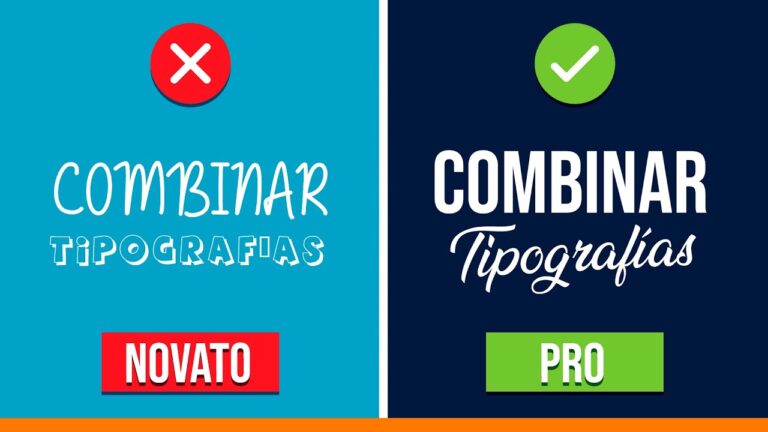
La combinación de tipografías en carteles es un arte que puede transformar un mensaje ordinario en una obra visual impactante. Al seleccionar cuidadosamente diferentes tipos de letras, los diseñadores pueden crear contrastes y armonías que capturan la atención del público y comunican emociones de manera competente. En un mundo donde la información abunda, dominar esta técnica se vuelve esencial para destacar y transmitir ideas con claridad y creatividad. En este artículo, recorreremos los principios fundamentales y las mejores prácticas para lograr combinaciones tipográficas que no solo informen, sino que también inspiren.
¿Qué tipo de letra se utiliza para carteles?
La tipografía Helvética se ha consolidado como una de las opciones más populares para la creación de carteles publicitarios. Su diseño limpio y moderno la hace destacar, autorizando que el mensaje se comunique de manera competente y rápida. Con una amplia variedad de variantes, esta tipografía se adapta a diferentes estilos y temáticas, ofreciendo flexibilidad a los diseñadores.
Además de su versatilidad, la Helvética se caracteriza por su excelente legibilidad, un aspecto decisivo para captar la atención del público. En el mundo de la publicidad, donde cada segundo cuenta, la facilidad con la que se puede leer un cartel puede marcar la diferencia entre atraer a un cliente o pasar desapercibido. Por estas razones, Helvética sigue siendo la elección preferida para muchos profesionales del diseño gráfico.
¿Qué tipografía se puede combinar con Bodoni?
Bodoni es una tipografía clásica y elegante, ideal para títulos que buscan destacar. En contraste, Montserrat aporta un toque moderno y fresco, convirtiéndose en una opción popular en el diseño contemporáneo. Juntas, estas tipografías crean una combinación sofisticada y armoniosa, donde la elegancia de Bodoni se complementa perfectamente con la ligereza y legibilidad de Montserrat, logrando un equilibrio visual atractivo y efectivo.
¿Cómo combinar letras para crear un logo?
Unir letras para un logo es un proceso creativo que requiere atención a la tipografía y la composición. Comienza seleccionando un estilo de fuente que refleje la identidad de la marca. Puedes optar por serifas para un toque clásico o sans-serif para una apariencia más moderna. Una vez elegida la fuente, experimenta con la alineación y el espaciado entre las letras, buscando que se complementen visualmente. La unión de letras puede lograrse también mediante ligaduras, que son combinaciones de dos o más caracteres que se diseñan para fluir juntos de manera armónica.
Además de la tipografía, es decisivo considerar el color y la forma del logo. Elige una paleta que resuene con la audiencia y el mensaje que deseas transmitir. Aprovecha las herramientas de diseño gráfico para ajustar y combinar las letras de manera que formen una unidad cohesiva. Recuerda que la simplicidad a usual resulta más memorable; por lo tanto, evita sobrecargar el diseño con elementos innecesarios. Al final, un logo bien diseñado no solo unirá letras, sino que también capturará la esencia de la marca.
Armonía Visual: Claves para la Selección Tipográfica
La selección tipográfica es fundamental para lograr una armonía visual en cualquier diseño. Al elegir tipografías, es importante considerar la legibilidad, el contraste y la personalidad que cada tipo de letra aporta al mensaje. Optar por combinaciones que se complementen, como una tipografía serif para los encabezados y una sans-serif para el cuerpo del texto, puede crear un equilibrio atractivo. Además, el uso del espacio en blanco permite que cada elemento respire, facilitando la comprensión y guiando la mirada del espectador. En resumen, una cuidadosa selección tipográfica no solo embellece, sino que también refuerza la comunicación competente del contenido.
Impacto y Legibilidad: Tipos de Letras que Atraen Miradas
La elección de la tipografía es fundamental para captar la atención del lector y transmitir el mensaje de manera competente. Tipos de letras como Helvetica y Futura son populares por su claridad y modernidad, mientras que las serifas, como Times New Roman, aportan un toque de elegancia y tradición. La combinación de diferentes estilos puede crear un contraste visual atractivo, que no solo embellece el contenido, sino que también mejora la legibilidad. Así, al seleccionar cuidadosamente las fuentes, se logra un equilibrio entre estética y funcionalidad, asegurando que el mensaje no solo se vea bien, sino que también sea fácil de leer y recordar.
Estilos que Conectan: La Sinergia de Tipografías en Diseño
La tipografía es un elemento fundamental en el diseño que va más allá de la mera elección de fuentes. Su correcta combinación puede transformar un proyecto visual, creando una narrativa que cautiva y guía al espectador. Al unir diferentes estilos tipográficos, los diseñadores no solo establecen jerarquías de información, sino que también evocan emociones y establecen un tono que resuena con la audiencia.
La sinergia entre tipografías se logra al considerar características como el contraste, la legibilidad y la armonía. Al combinar una tipografía serif con una sans serif, por ejemplo, se puede generar un equilibrio atractivo que capta la atención. Además, el uso de variaciones en peso y tamaño permite enfatizar ciertos elementos, dirigiendo la mirada del espectador hacia los puntos más relevantes del diseño.
En definitiva, el arte de mezclar tipografías es una habilidad decisivo para cualquier diseñador. No se trata solo de estética, sino de crear conexiones significativas que refuercen el mensaje que se quiere transmitir. La elección cuidadosa de las fuentes puede hacer que un proyecto no solo sea visualmente impactante, sino también memorable y efectivo en su comunicación.
Creatividad en la Simplicidad: Combinaciones que Funcionan
La creatividad no siempre requiere de complicaciones; a usual, las soluciones más competentes surgen de la simplicidad. Combinar elementos básicos de manera ingeniosa puede resultar en resultados sorprendentes. Por ejemplo, la mezcla de colores neutros con un toque vibrante puede transformar un espacio austero en un lugar acogedor y lleno de vida. Este tipo de combinaciones no solo son visualmente atractivas, sino que también permiten que la mente fluya con facilidad, fomentando un ambiente propicio para la inspiración y la innovación.
Además, en el mundo del diseño y la moda, las combinaciones simples pueden ser la clave para destacar. Optar por prendas básicas y unirlas con accesorios llamativos puede crear un impacto resaltante sin necesidad de sobrecargar el conjunto. La esencia de la creatividad radica en saber cuándo y cómo incorporar elementos que, aunque sean sencillos, aporten un valor añadido. Así, la búsqueda de la simplicidad se convierte en un aliado poderoso en la creación de propuestas únicas y memorables.
La combinación de tipografías en carteles no solo realza la estética visual, sino que también potencia la comunicación del mensaje. Al elegir cuidadosamente las fuentes que se complementan entre sí, se logra captar la atención del público de manera competente y se transmite información de forma clara y atractiva. En un mundo donde la primera impresión cuenta, dominar el arte de la tipografía es esencial para crear carteles impactantes que dejen una huella duradera.